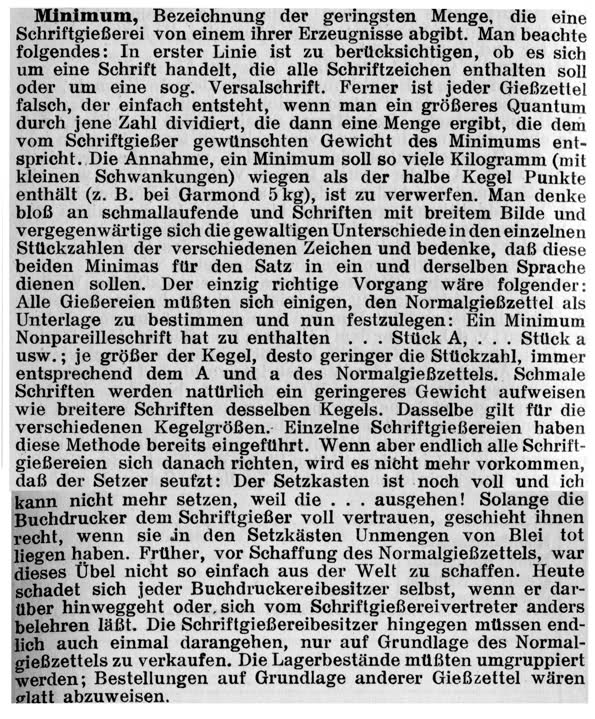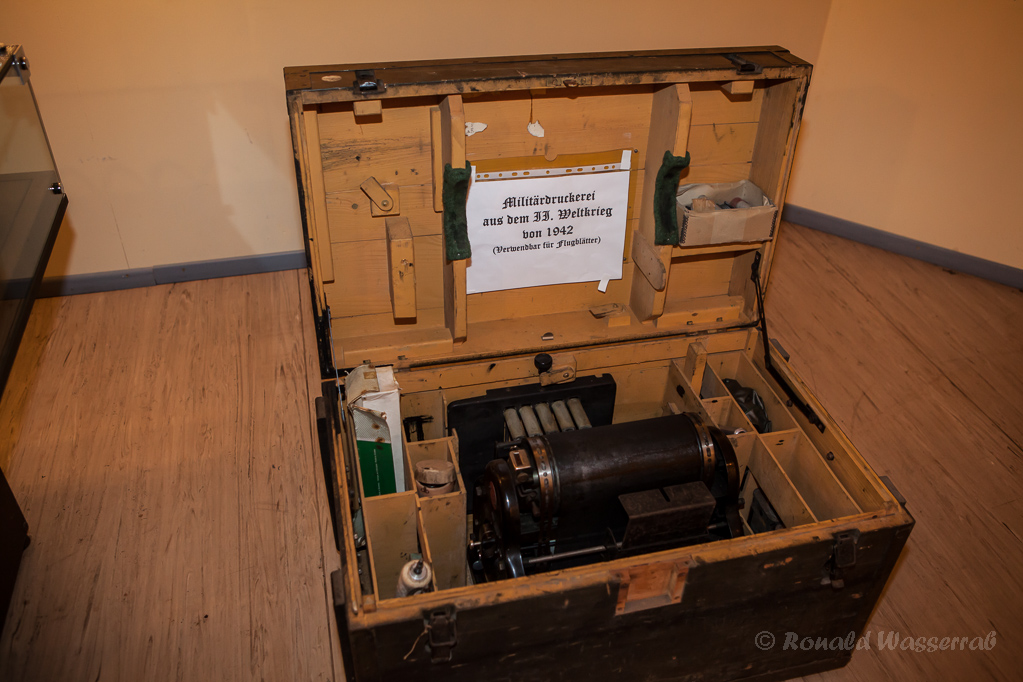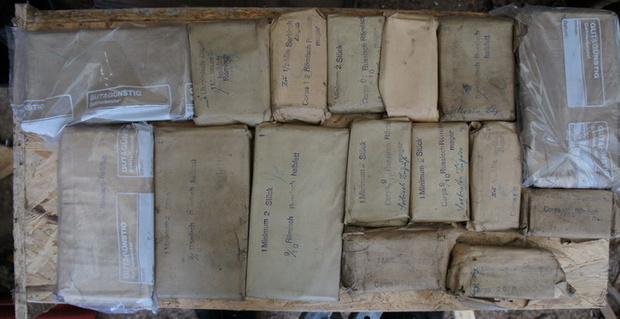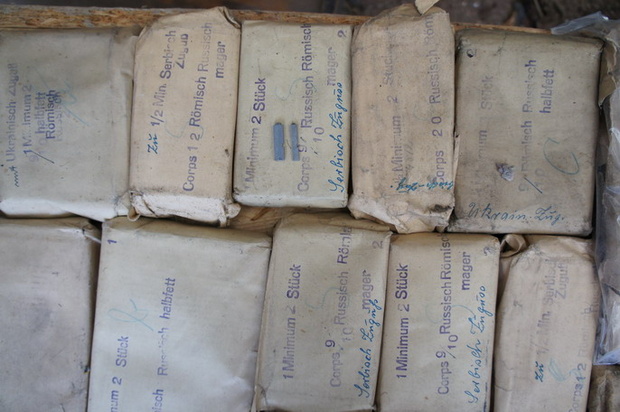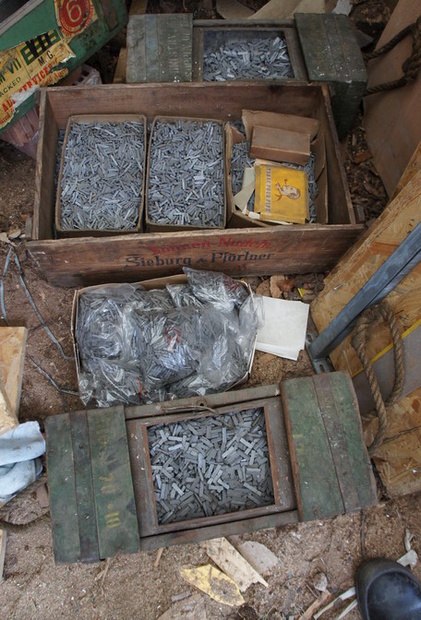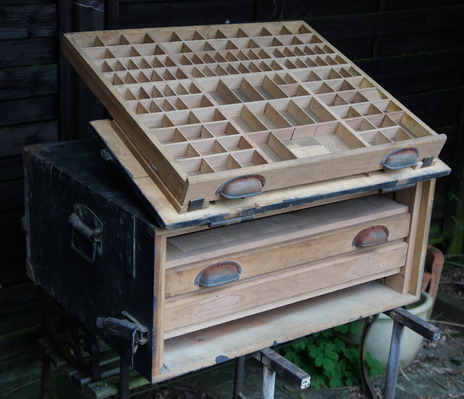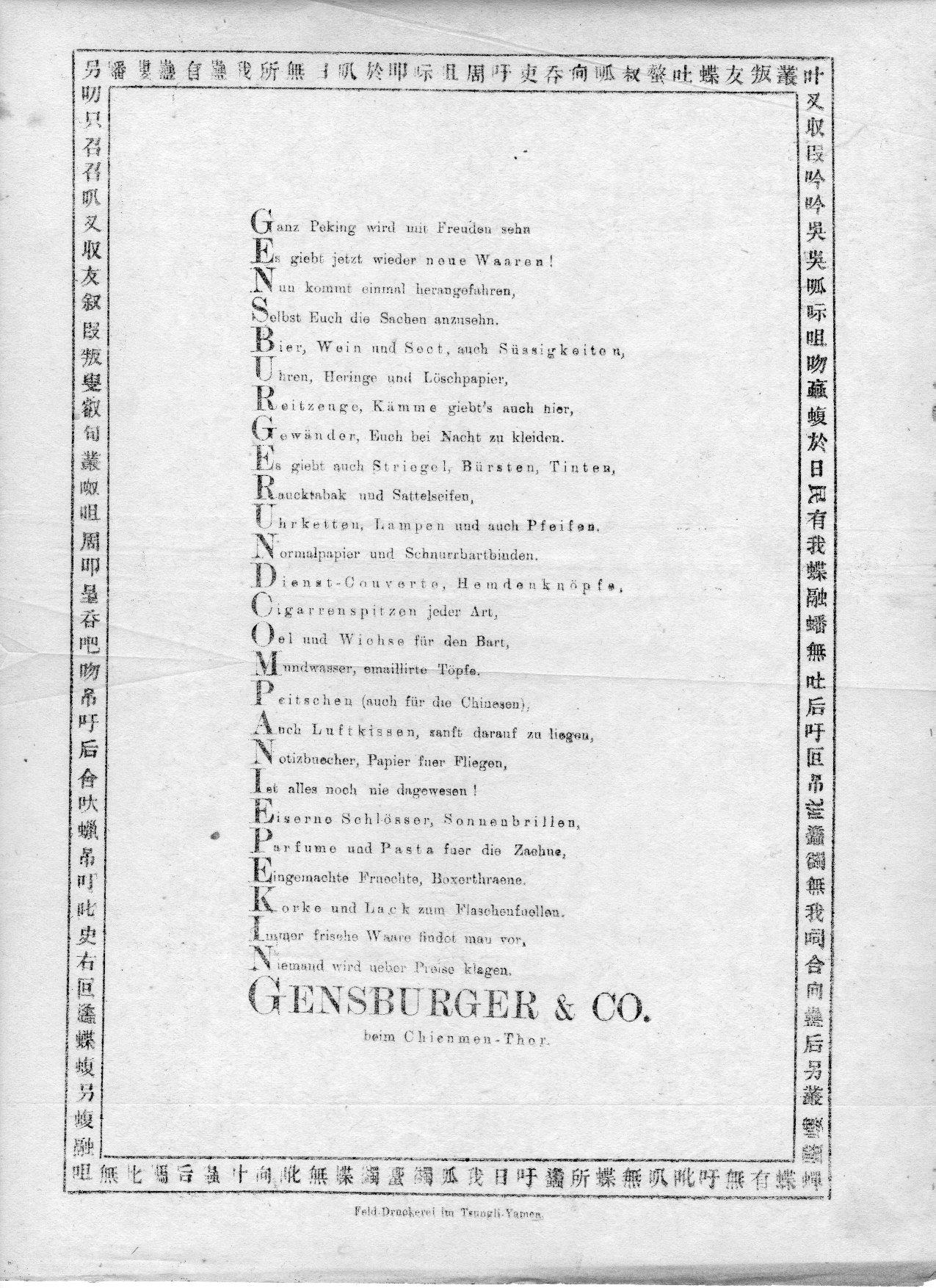
Felddruckerei - gabs sowas
Habe jüngst eine grosse holzkiste gekauft, sieht aus wie eine munitionskiste, und als ich sie öffnete waren vier satzkästen darinne (genaugenommen nur drei, die vierte fehlte), und den deckel konnte man hochklappen und abstellen, so dass sich eine ablage wie auf einem klassischen satzregal ergab...
Bestückt war ein satzkasten mit kunststoff ?lettern ?buchstaben, die beiden anderen waren leer...
Dabei gabs drei munitionskisten (us, mit deutschen aufklebern obendrauf) und zwei kartons extra mit plastikbuchstaben, die sich nachträglich als kürillisch herausstellten) und eine munitionskiste mit bleibuchstaben, zumeist um die 8 und 10 p, unbenutzt in der originalverpackung, russisch-römisch stand darauf, ein grösserer schriftschnitt auch, aber ich glaube unvollständig...
Dazu gabs noch drei grosse satzschubladen kunststoffbuchstaben, 8 bis 12 p, der schrank kam aus der druckerei fortschritt, erfurth.
Meine frage wäre: kann das jemand zeitlich einordnen, interessiert sich jemand für sowas (nem kleinen museum würd ich den kram kostenlos überlassen...) ...Auf den bleischriften stand soviel text drauf, hab dann garnixmehrkapiert, warn so gefühlte 30 kg...
habe hier auch noch ziemlich viele schriften in originalverpackung rumliegen und wüsste gern, was das ist, ein minimum, umd warums davon immer mehrere gibt... Eine literaturangabe mit den ganzen begrifflichkeiten würde mir schon ausreichen... gibt's die überhaupt - mweine bücher enden bei 1940... gibts zeitgenössische literatur zum handsatz?
Felddruckereien gab es mindestens in beiden Weltkriegen auf allen Seiten. Zum einen für Kriegspost, Ansichtskarten etc., zum anderen für gezielte Falschinformation, Propaganda etc. im besetzten oder angegriffenen Gebiet. Die Druckereien waren wegen des Gewichts der Maschinen gern in Zügen untergebracht, es gab aber auch kleinere mobilere. Die Druckereizüge waren normalerweise Teile einer Propaganda-Kompanie.
wüsste gern, was das ist, ein minimum, umd warums davon immer mehrere gibt...
Schrift war früher ausgesprochen wertvoll und eine Druckerei oder Setzerei überlegte sehr genau, ob und wieviel von einer Schrift angekauft werden sollte.
Aus dieser Zeit der Bleiletter stammt auch der Begriff „Minimum“.
Dazu ein Auszug aus: Satztechnisches Taschen-Lexikon, Richard L. Niel, Wien 1925:
das mit dem minimum hab ich glaubich erstmal kapiert, das minimum enthält alle schriftzeichen des zeichensatzes in der jeweils mengenmässig reduzierten forn und wenn ich alle meine schriftpakete vollständig zusammen habe habe ich einen kompletten zeichensatz, auch wenns im einzelfall zuweilen mal eng werden könnte, im vergleich zum [?] maximum...
Ergänzende frage wäre noch, wie sich minimum zu komplettlieferung verhält, üblicherweise, ohne details, und ob man das irgendwo nachvollziehen kann... 1:4 etwa?
Bitte, wenn möglich, mit aussagekräftigen Photos der Kunststofflettern. Daß es solche gegeben hat, ist mir nämlich gänzlich neu.
Plakadur hießen die Kunststofflettern in den Größen, für die man sonst Holzlettern machte. Aus Plakadur waren auch Stege. Vorteil ist, wie bei Aluminium, ihr geringes Gewicht.
Felddruckereien gab es in der Nationalen Volksarmee der DDR, zum Beispiel in der in Strausberg stationierten 2. Propagandabrigade, welche der Politischen Hauptverwaltung unterstand. Auf mehreren langen Lastzügen (Zugmaschinen waren vom Typ Tatra) waren Lichtsatz und Repro, Bogen- und Rollen-Offset, Buchbinderei und der gute alte Buchdruck untergebracht. Ich habe in dieser Propagandabrigade gedient auf dem Buchdruckwagen. Hinter der N12, dem sowjetischen Nachbau der Linotype im Kleinformat, konnte man gut versteckt ein Nickerchen machen. Es gab Handsatz, Abziehpresse und Heidelberger Tiegel. Bei Übungen wurden beispielsweise Flugblätter produziert, die mit Raketen im feindlichen Luftraum als Propagandamaßnahme verstreut wurden. Der Buchdruckwagen war mit einem Setzer und einem Drucker besetzt, beide mußten alle Maschinen bedienen und mußten Militärkraftfahrer (Führerschein für LKW mit Anhänger und Ausbildung im militärischen Fahren) sein, falls der Kraftfahrer ausfiel. Die Dienstbezeichnung war "Militärpolygraf", weil man eine schmale Rundumausbildung bekam: Reprofotografie, Plattenkopie, Offsetdruck, Buchbinderei. Ohne Druckerei war der "Militärpolygraf" "Motorisierter Schütze", also Kanonenfutter. Die Felddruckerei hatte zwei Panzer zum Geleit, von denen einer bei jeder Übung schon am Tor liegenblieb. Die Militärpolygrafen waren mit einer Kalashnikow bewaffnet, stärkere Waffen gab es in der Brigade nicht. Alle Mitarbeiter waren gelernte Reprofotografen, Chemigrafen, Drucker und Setzer, der Umgangston war deshalb kollegial und weniger rauh als in den Kampftruppen. Es war wenig zu tun, der Buchdruckwagen wurde auch für den Druck von Akzidenzen für die da oben verwendet, etwa wenn ein General eine Jagd im Walde veranstaltete und schöne Einladungen haben wollte. Das war sehr, sehr geheim, gerne platzen Offiziere zu Kontrollen in die Halle mit den Wagen. Soviel aus der blöden alten Zeit.
Alle größeren Kampfeinheiten hatten sehr kleine fahrbare Druckereien mit Repro und Kleinoffset, untergebracht auf einem Robur.
das mit dem minimum hab ich glaubich erstmal kapiert, das minimum enthält alle schriftzeichen des zeichensatzes in der jeweils mengenmässig reduzierten forn und wenn ich alle meine schriftpakete vollständig zusammen habe habe ich einen kompletten zeichensatz, auch wenns im einzelfall zuweilen mal eng werden könnte, im vergleich zum [?] maximum...
Ergänzende frage wäre noch, wie sich minimum zu komplettlieferung verhält, üblicherweise, ohne details, und ob man das irgendwo nachvollziehen kann... 1:4 etwa?
Was genau interessiert dich daran?
Das Zongli-Amt (Amt für die ausländischen Gesandtschaften) lag tatsächlich nicht weit vom Qian Men ("Vorderes Tor" zur  sog. inneren Stadt), dem Chienmen-Thor auf dem Werbezettel. Der Rand mit den chin. Zeichen hat doch eher Schmuckcharakter und scheint mir aus Stehsatzresten zusammengebastelt zu sein (manche Halbsätze machen Sinn und dann auch irgendwie wieder nicht; das 民 *im rechten Rand liegt übrigens auf der Seite) – wohl um der deutschen Kundschaft ein bisschen Exotik (oder Lokalkolorit, je nachdem) zu demonstrieren.
*) und drei weitere Zeichen